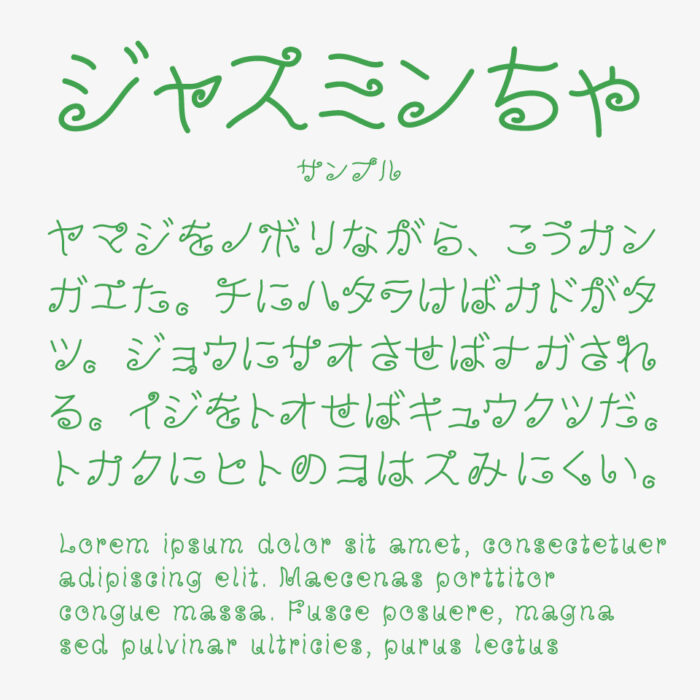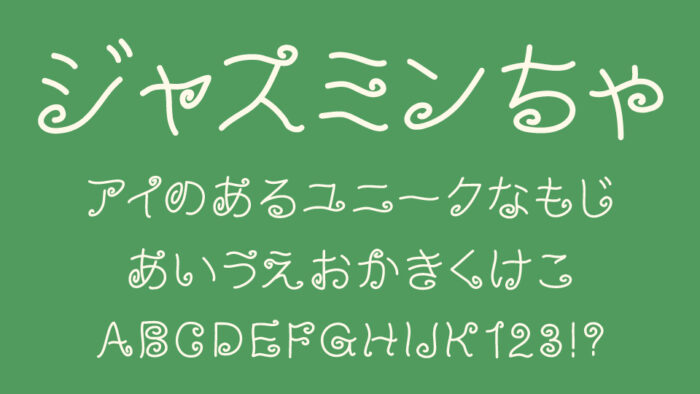
ジャスミンちゃフォントは、「茉莉龍珠(ジャスミンドラゴンパール)」をイメージして作った、オリエンタルな雰囲気なデザインフォントです。
文字の一部に「茉莉龍珠」の特徴でもあるクルンとしたカーブが添えられていて、可憐でオーガニックな雰囲気を漂わせています。
手書き文字のようなやわらかい印象で、遊び心のある装飾が目を引くため、アクセントにぴったりなデザインフォントです。
収録文字は、ひらがな・カタカナ・アルファベット・数字・記号が収録されています。